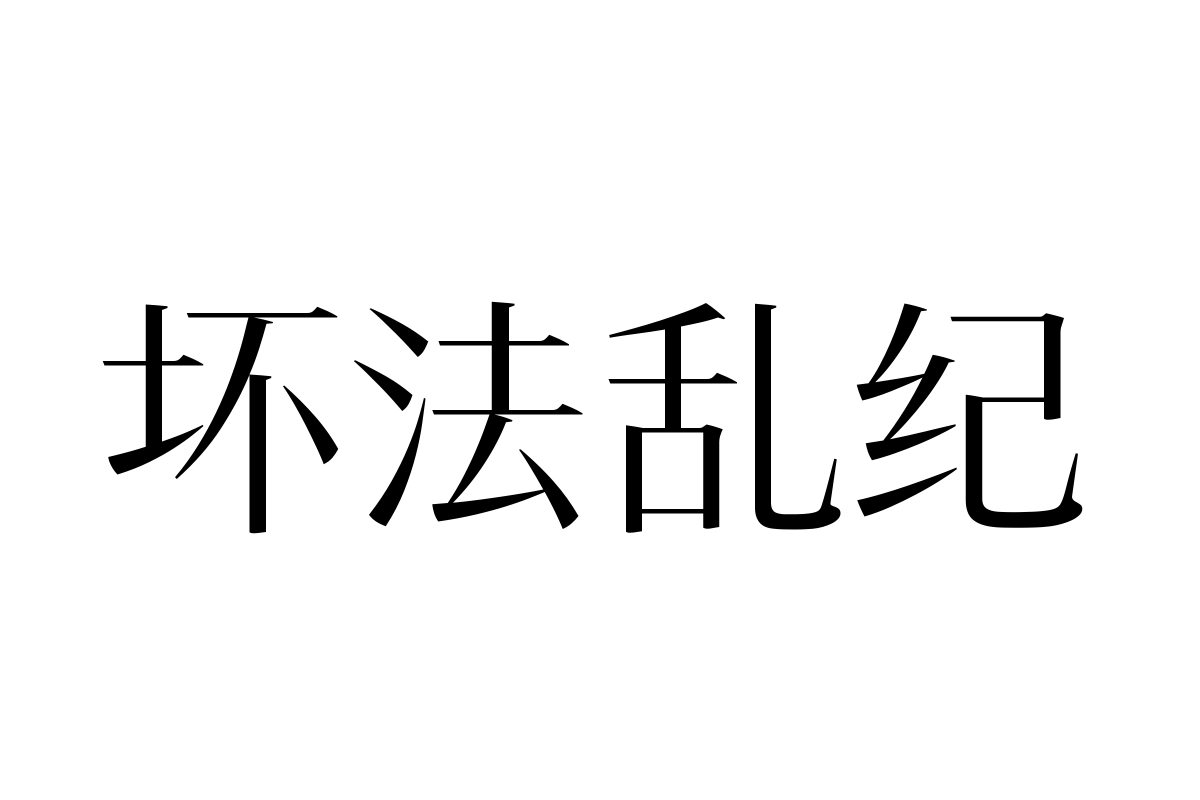
汉仪瑞意宋_45W 是一款由汉仪公司设计的字体,主要用于商业和正式的文档中。这款字体的特点是字形规整,线条流畅,给人一种庄重、大气的感觉。其特点是笔画粗细分明,结构严谨,非常适合用于制作印刷品、名片、广告等需要展现专业形象的场合。
此外,汉仪瑞意宋_45W 字体的字号范围广泛,从小到大都可以完美适配,无论是大幅面的广告设计还是小型的名片设计,都能轻松应对。同时,这款字体还具有很好的可读性,即使在远距离观看也能保证文字的清晰可见。
总的来说,汉仪瑞意宋_45W 是一款非常实用的商务字体,无论是在设计还是在印刷方面,都能展现出其独特的魅力。